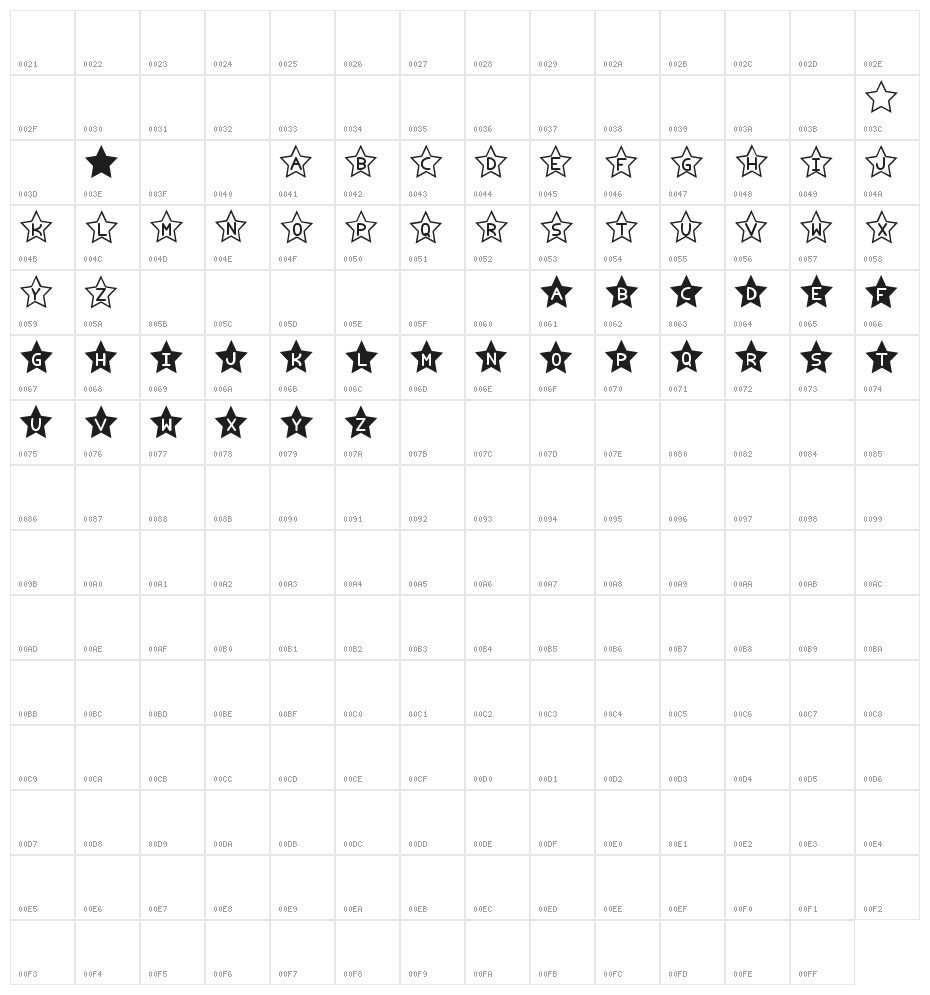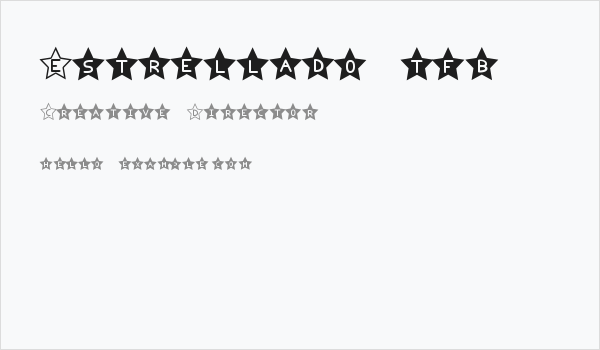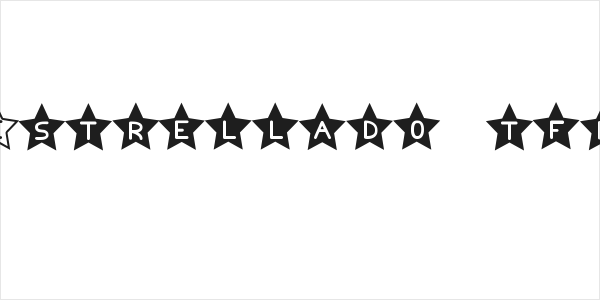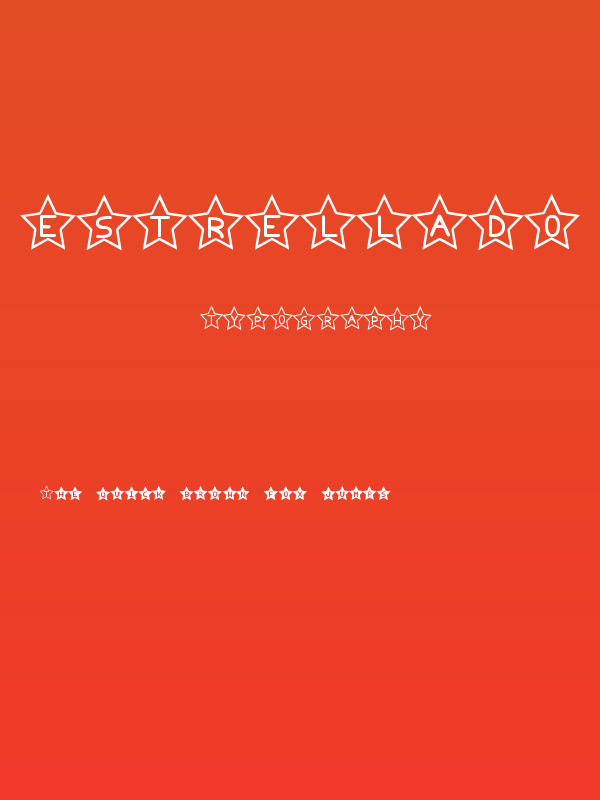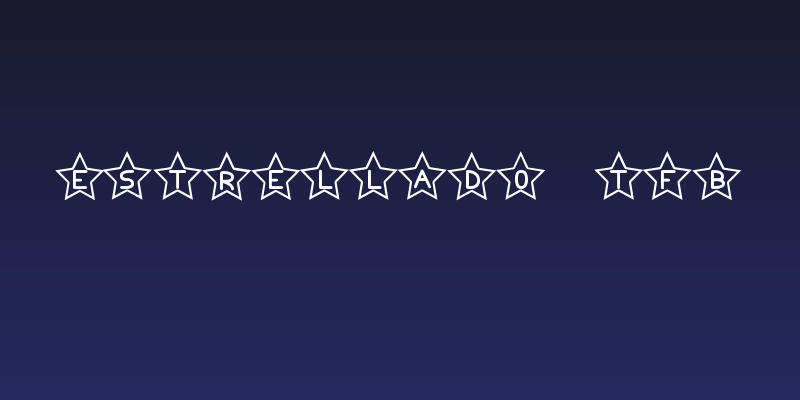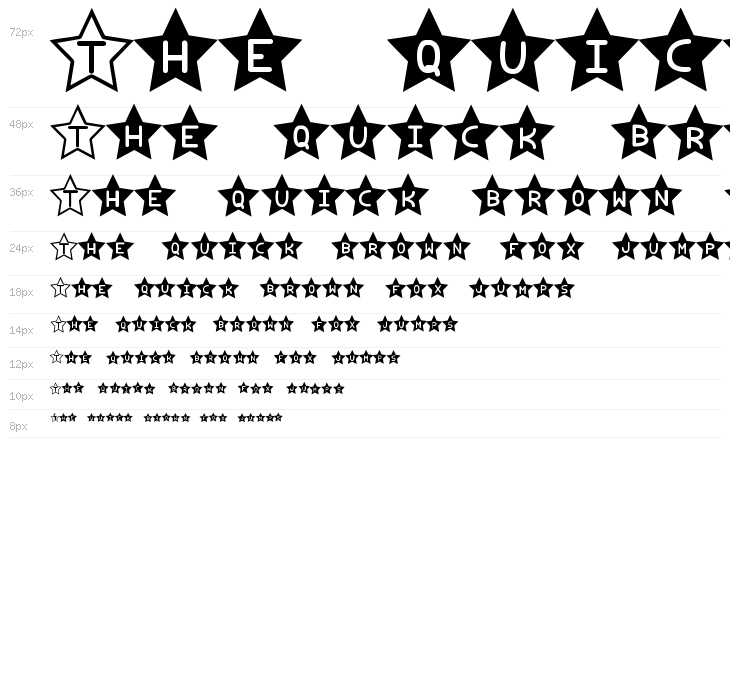
Estrellado tfb Font
✎ Decorative
| Vorgeschlagene Projekte | Ideal for party invitations, children's book covers, festive banners, and playful branding. |